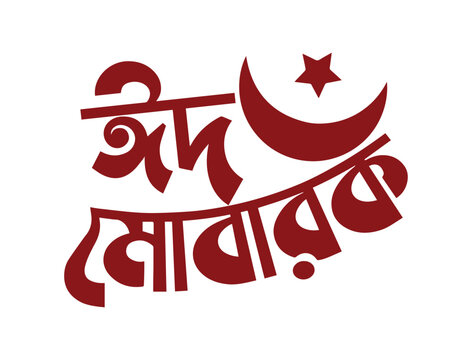
Bangla Font for Adobe Premiere Pro: Enhance Your Video Editing
Bangla Font for Adobe Premiere Pro: Ultimate Guide to Perfect Typography
বাংলা ফন্ট Adobe Premiere Pro-তে: সহজ গাইড এবং ৫টি সেরা ফন্ট বিশ্লেষণ
ভিডিও এডিটিং এখন শুধু বিনোদনের জন্য নয়, পেশাগত কাজেও প্রয়োজনীয় হয়ে উঠেছে। Adobe Premiere Pro হল ভিডিও এডিটরদের জন্য সবচেয়ে জনপ্রিয় সফটওয়্যারগুলোর একটি। কিন্তু যারা বাংলা ভাষায় ভিডিও বানাতে চান, তাদের জন্য ফন্ট সিলেকশন একটা বড় চ্যালেঞ্জ। অনেকে জানেন না, কিভাবে Premiere Pro-তে বাংলা ফন্ট ব্যবহার করতে হয়, বা কোন ফন্টগুলো ভালোভাবে কাজ করে। আজকের এই লেখায় আমরা শিখব—কিভাবে সহজে Premiere Pro-তে বাংলা ফন্ট সেটআপ করবেন, কোন ৫টি ফন্ট সবচেয়ে উপযোগী, এবং কোন সমস্যা হলে কী করবেন।
বাংলা ভাষায় ভিডিও তৈরি করা মানে শুধু বাংলা ভাষায় স্ক্রিপ্ট লেখা নয়, আরও গভীর কিছু। আপনি যদি বাংলা ভাষায় কিছু বলেন বা লিখেন, সেটি দেখানোর জন্য সুন্দর ফন্ট দরকার। কারণ, ফন্টের স্টাইল, স্পষ্টতা আর মান একসাথে না থাকলে ভিডিওর বার্তা ঠিকমতো পৌঁছায় না। অনেক সময় দেখা যায়, ভালো ভিডিও বানিয়েও শুধু ফন্টের জন্য দর্শকের চোখে পড়ে না। তাই Premiere Pro-তে বাংলা ফন্ট ব্যবহার শেখা, সঠিক ফন্ট চেনা এবং সমস্যা সমাধান জানা এখন টেকনিক্যাল স্কিলের অংশ হয়ে গেছে।
অনেকে শুরুতে ভয় পান—বাংলা ফন্ট বুঝি শুধু ফটোশপ বা ইলাস্ট্রেটরে ভালো চলে, Premiere Pro-তে ঝামেলা বেশি। কিন্তু বাস্তবতা হচ্ছে, কিছু স্মার্ট টিপস মেনে চললে Premiere Pro-তে বাংলা ফন্ট ব্যবহার খুব সহজ। আপনি যদি নতুন ইউজার হন, অথবা আগে শুধু ইংরেজি ফন্ট ব্যবহার করতেন—এই গাইড আপনাকে ধাপে ধাপে শেখাবে, বাংলা ফন্টে ভিডিও এডিটিং করা কতটা সহজ হতে পারে।
এছাড়াও, আজকের লেখায় ৫টি বেস্ট বাংলা ফন্টের গভীর বিশ্লেষণ পাবেন—কোন ফন্ট কোথায় সবচেয়ে মানায়, কোন ফন্টে কী সমস্যা হয়, আর পেশাদাররা কোন ফন্ট বেছে নেন। সাথে থাকবে রিয়েল লাইফ উদাহরণ, প্রো টিপস, কপিরাইট বিষয়ে সতর্কতা, আর ফন্ট সিলেকশনের গোপন কলা-কৌশল। শেষ পর্যন্ত পড়লে, বাংলা ফন্টের জগতে আপনি হয়ে যাবেন অনেকটাই আত্মবিশ্বাসী।
Premiere Pro-তে বাংলা ফন্ট কেন গুরুত্বপূর্ণ
বাংলা ভাষায় ভিডিও বানাতে গেলে শুধু ভাষা জানলেই হয় না—সঠিক ফন্ট বাছাই করাও জরুরি। কারণ, ফন্টের মাধ্যমে আপনার ভিডিওর টেক্সট আরও আকর্ষণীয়, পড়তে সহজ এবং পেশাদারী লাগে। বাংলা ফন্ট সঠিকভাবে না বসলে টেক্সট গুলিয়ে যেতে পারে, অক্ষর ভেঙে যেতে পারে বা ভিডিওর মান কমে যেতে পারে।
অনেক সময়ই দেখা যায়, ভাষা সুন্দর কিন্তু ফন্টের কারনে বানান ভেঙে গেছে, কিংবা কার বা যুক্তাক্ষর ঠিকমতো বসেনি। বিশেষ করে যারা ইউটিউব বা সোশ্যাল মিডিয়াতে ভিডিও দেন, তাদের জন্য স্পষ্টতা আর আকর্ষণীয়তা অনেক বড় বিষয়। শুধু ভিডিওর ভেতরের টেক্সট নয়, থাম্বনেইল, টাইটেল, সাবটাইটেল—সবখানেই ফন্টের ভূমিকা সমান।
প্রফেশনাল ভিডিও এডিটররা যেমন Adobe Premiere Pro ব্যবহার করেন, তেমনি ইউটিউবার, ফেসবুক কন্টেন্ট ক্রিয়েটর, কিংবা শিক্ষামূলক ভিডিও নির্মাতাদের জন্যও বাংলা ফন্টের গুরুত্ব অপরিসীম। সঠিক ফন্ট মানে ভিউয়ারের চোখে পজিটিভ ইমপ্রেশন, স্পষ্ট বার্তা, আর ব্র্যান্ডিং-এ বাড়তি সুবিধা।
ধরা যাক, আপনি একটি শিক্ষামূলক ভিডিও বানাচ্ছেন। যদি ফন্ট অস্পষ্ট হয়, ছোট অক্ষর গুলিয়ে যায়, তাহলে ছাত্র-ছাত্রীরা বারবার ভিডিও থামিয়ে দেখতে বাধ্য হবে। এতে শেখার আগ্রহ কমে যাবে। আবার যদি ব্র্যান্ড বা কোম্পানির ভিডিও বানান, তখন ফন্ট মানে আপনার পেশাদারিত্বের পরিচয়। বড় বড় ব্র্যান্ড যেমন Apple, Samsung, কিংবা Walton—সবাই তাদের ব্র্যান্ডিং ফন্ট নিয়ে খুব সিরিয়াস। কারণ, ফন্টই অনেক সময় ব্র্যান্ডের পরিচয় তৈরি করে।
আরেকটি বিষয় হচ্ছে, বাংলা ফন্ট এখন শুধু বাংলাদেশ নয়, ভারতের পশ্চিমবঙ্গ, আসাম, ত্রিপুরাসহ বিশ্বের নানা প্রান্তে প্রয়োজন হচ্ছে। যারা বিদেশে থাকেন, তাদের জন্য ভিডিওর ফন্ট আর ভাষা যেন সহজে বোঝা যায়, সেই দিকেও খেয়াল রাখতে হয়। তাই শুধু সুন্দর ফন্ট নয়, ইউনিকোড সাপোর্ট, স্পষ্টতা এবং কনটেন্টের ধরন অনুযায়ী ফন্ট নির্বাচন আজকের যুগে বিশেষ জরুরি।
প্রথমবার ভিডিও বানানোর সময় অনেকেই ভাবেন, যেকোনো বাংলা ফন্ট হলেই চলবে। কিন্তু একটু অভিজ্ঞতা হলে বোঝা যায়, সঠিক ফন্ট বাছাই করাটা ভিডিওর চেহারা সম্পূর্ণ বদলে দিতে পারে। যেমন, ফান কনটেন্টে হ্যান্ডরাইটিং ফন্ট দিলে ব্যক্তিগততা আসে, আবার নিউজ বা ডকুমেন্টারিতে ক্লিন ফন্ট দিলে সিরিয়াস লুক পাওয়া যায়। কাজেই, Premiere Pro-তে বাংলা ফন্টের সঠিক ব্যবহার মানে কনটেন্টের শক্তি বাড়ানো।